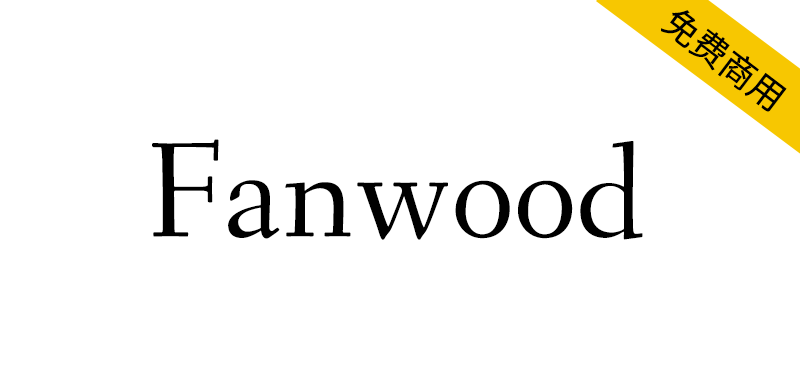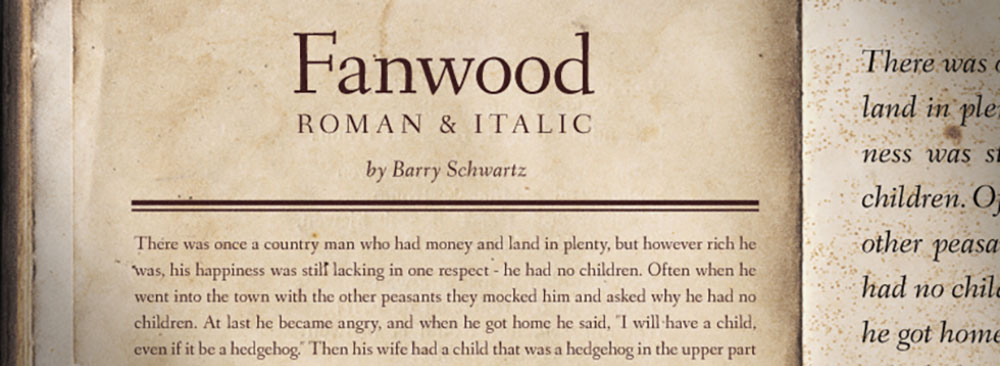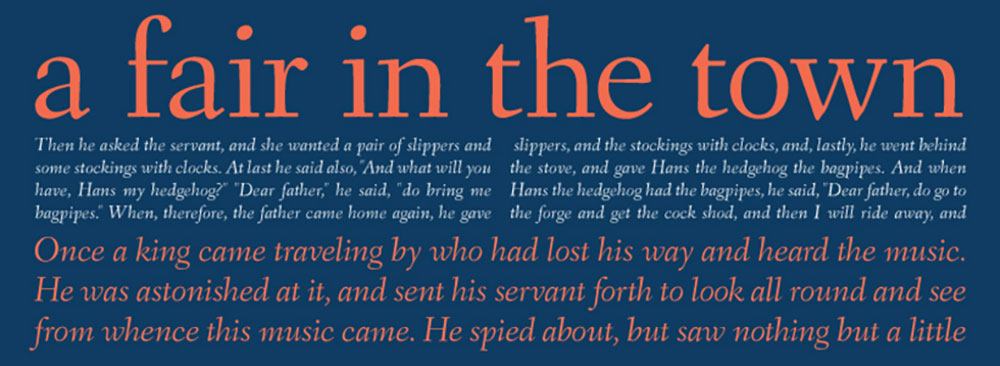
Fanwood是基于一位著名捷克裔美国字体设计师昔年的作品设计的衬线字体,包含正体与斜体两种样式。
Based on work of a famous Czech-American type designer of yesteryear. The package includes roman and italic.